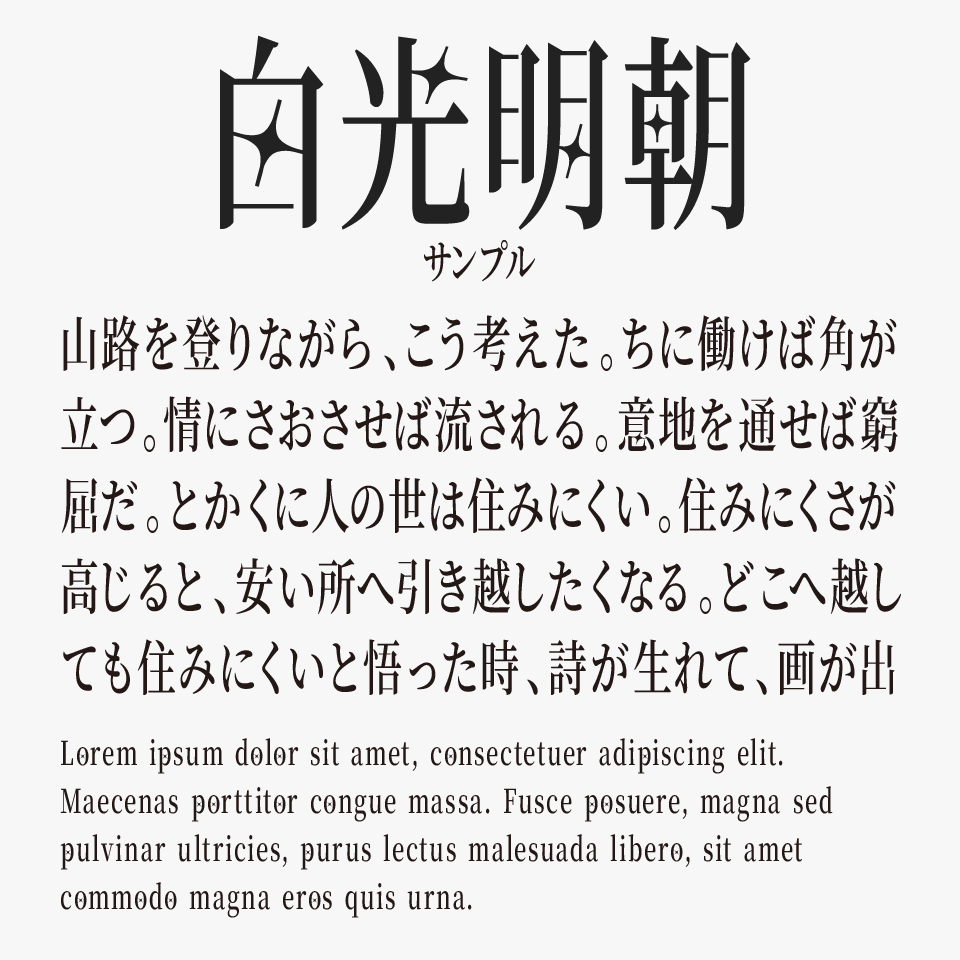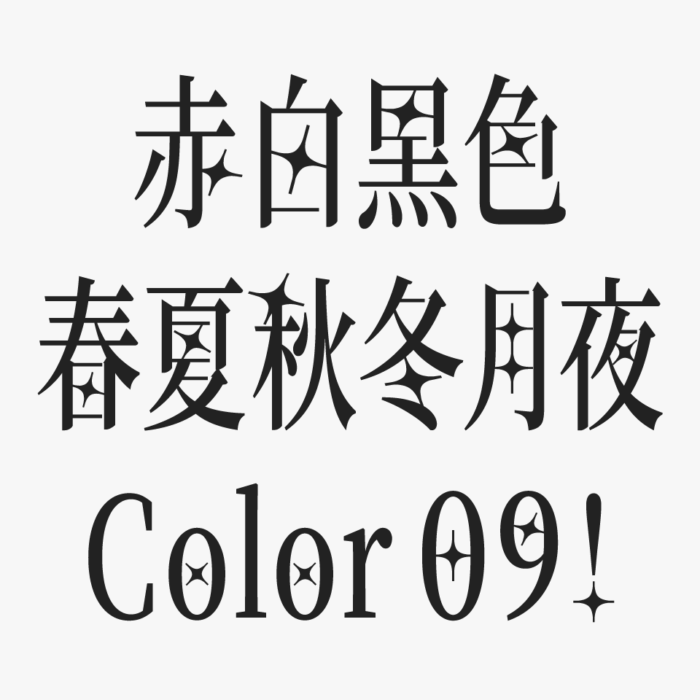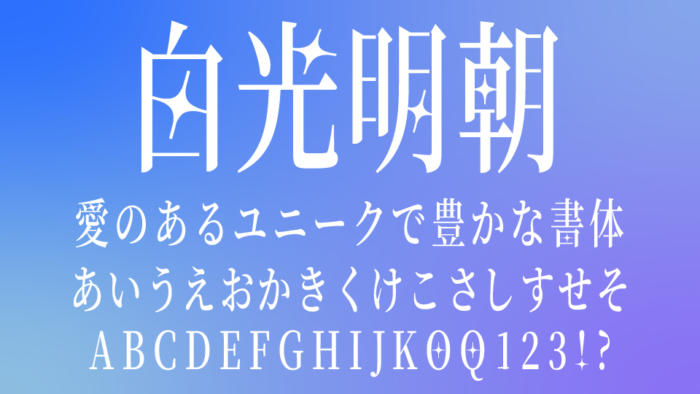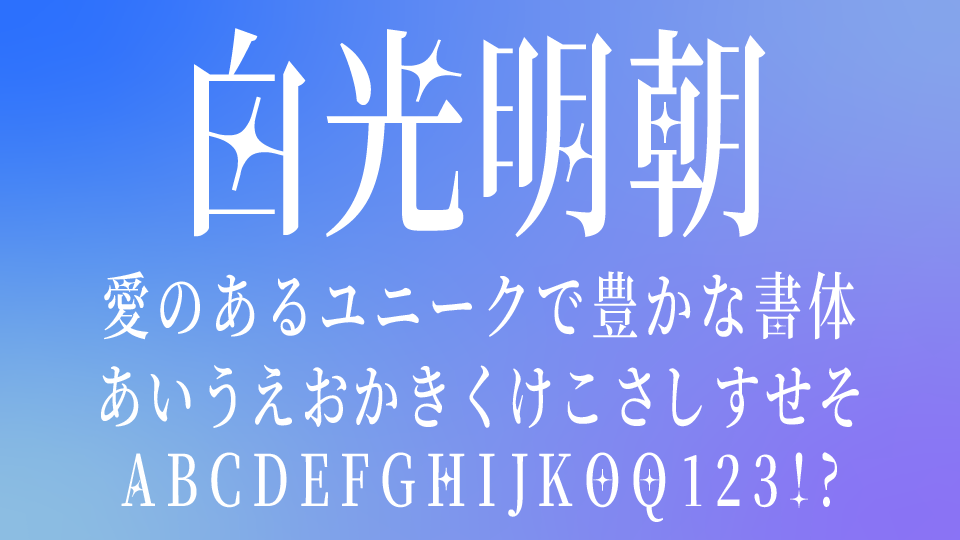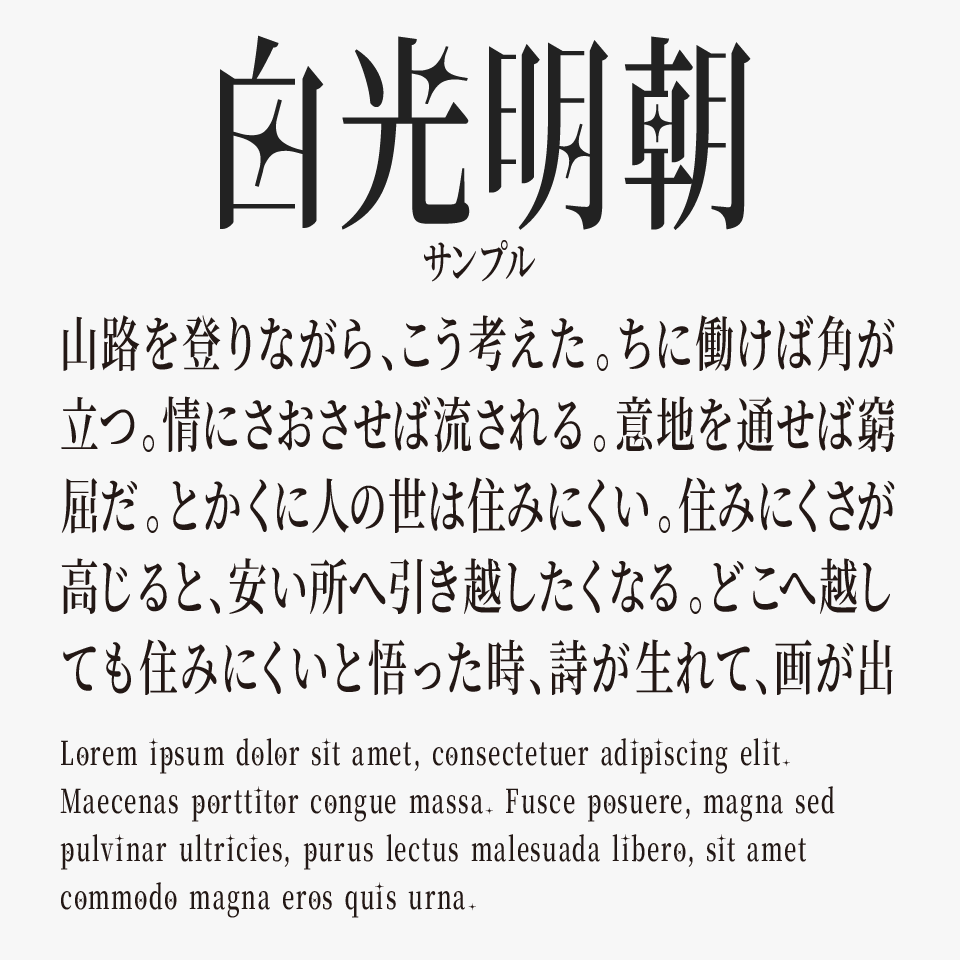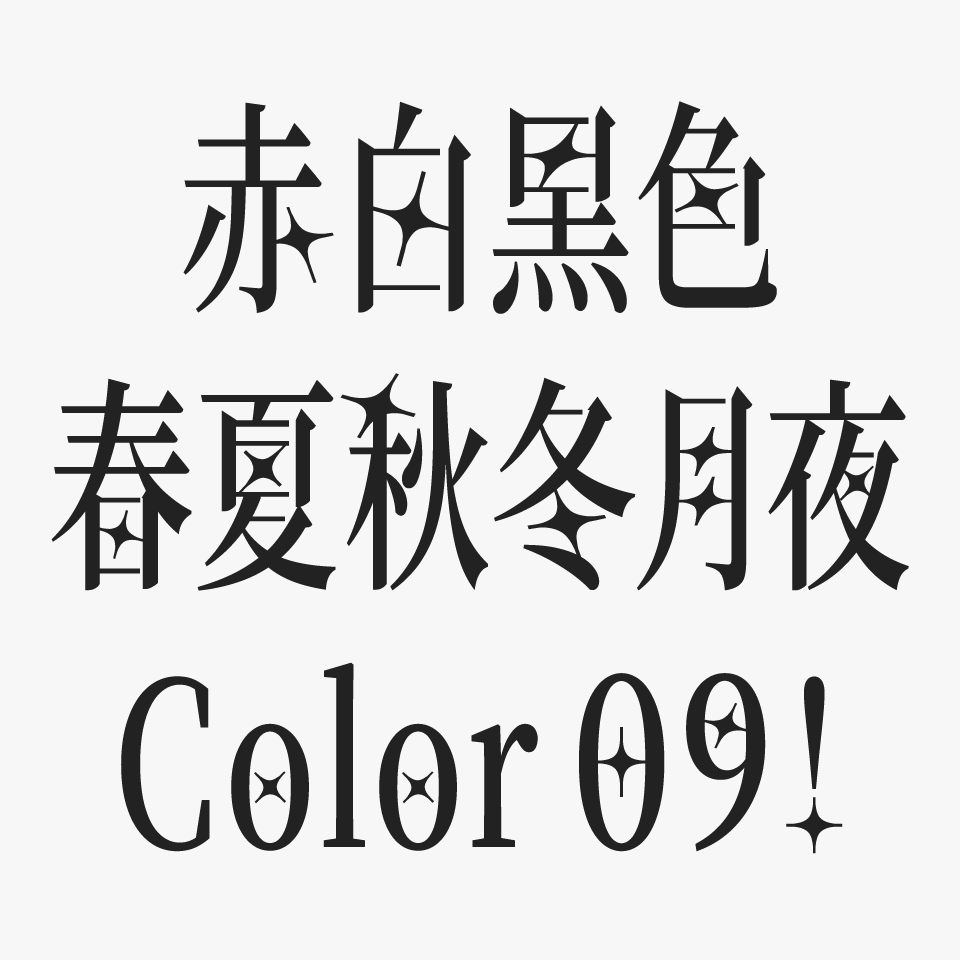
白光明朝フォントは、Noto Serifをベースにしながら、長体+スリット加工を加え、ところどころにキラリとした星の装飾された個性的な明朝体フォントです。
星のモチーフは一部の文字にだけ散りばめられており、文章を打ち込むとさりげなく星が現れ、幻想的な雰囲気を楽しめるフォントです。
また、長体とスリット加工によって、シャープな縦画と繊細な横画のコントラストが際立ち、クラシックな明朝体の佇まいの中にさりげないきらめきを感じられるフォントです。
星の形もさまざまで、星が入っている文字を見つける楽しさがあるフォントです。今後のアップデートで星入りの文字が増える予定とのことで、こちらも楽しみなポイントです。